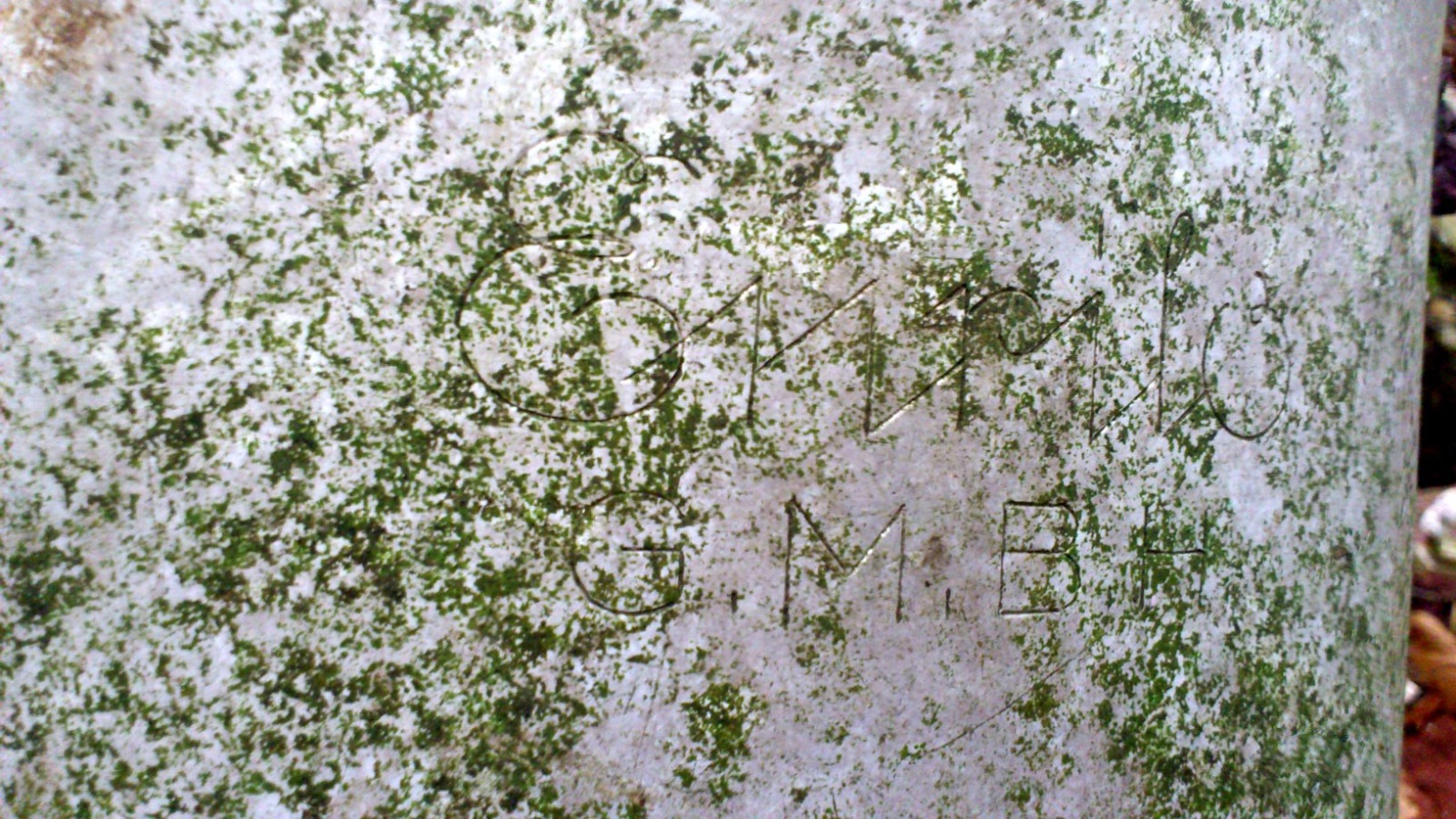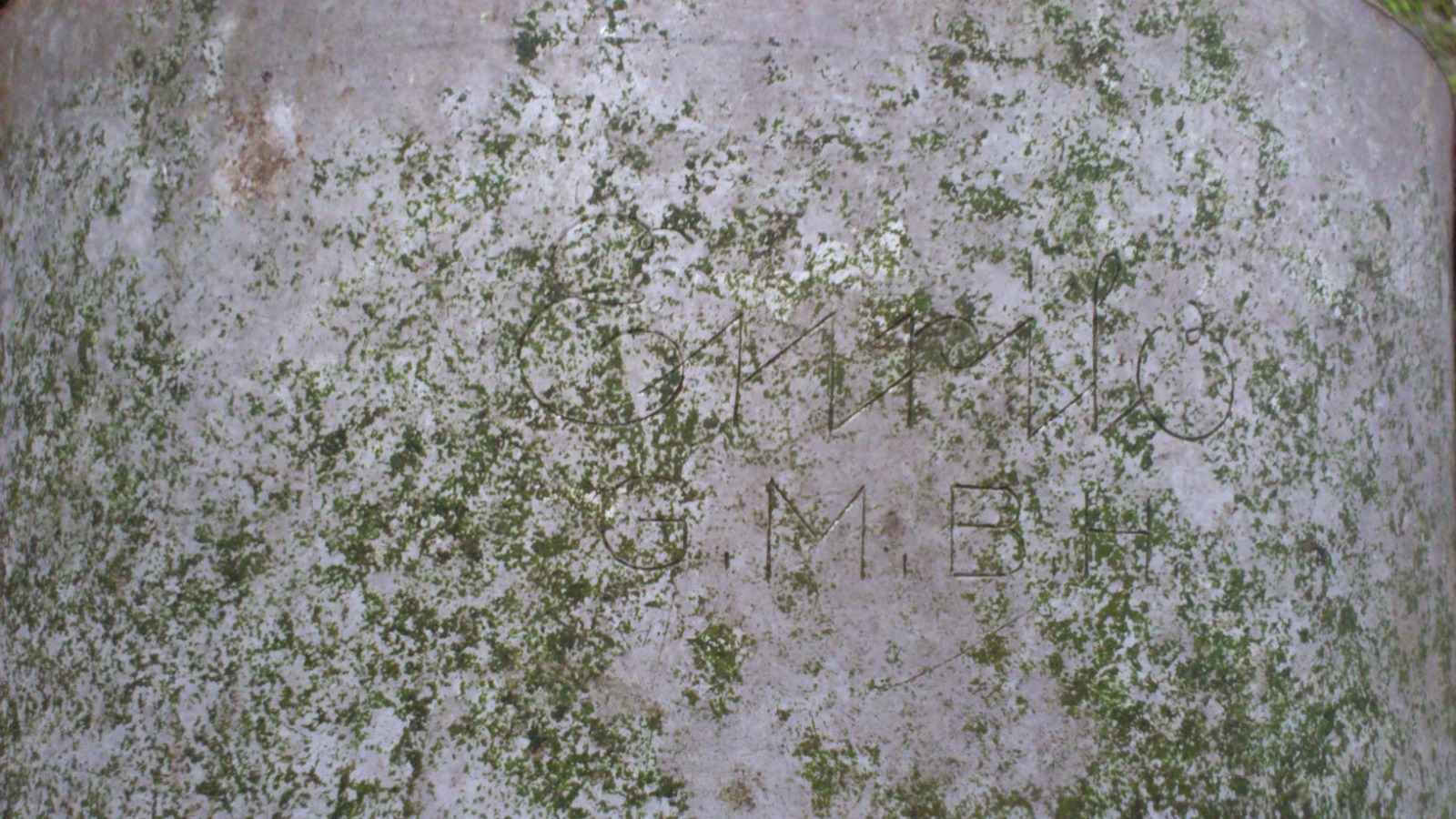
Schriftzug in Sütterlin?
Ich habe neulich im Wald einen uralten Topf gefunden, auf dem der Firmenname in Sütterlin eingestanzt war. Ich kann aber einige der Zeichen nicht zweifelsfrei identifizieren und bin mir mittlerweile nicht mal sicher, ob es überhaupt Sütterlin ist. Insbesondere der erste Buchstabe, der eigentlich nur ein "E" sein kann, müsste in Sütterlin ganz anders aussehen. Der zweite Buchstabe müsste ein "e" sein, dann würde der Firmenname aber mit "Ee" beginnen, was mir etwas komisch vorkommt. Beim zweitletzten Buchstaben war ich mir dann auch irgendwann nicht mehr sicher, ob es wirklich ein "l" ist.
Enpilo? Eepilo? Enpifo? Kann es jemand eindeutig identifizieren?
yep, das ist kein Sütterlin. Die Enrilo GmbH hat Kaffeesurrogate hergestellt, man findet auf ebay und Konsorten einige Blechdosen, Schilder etc.